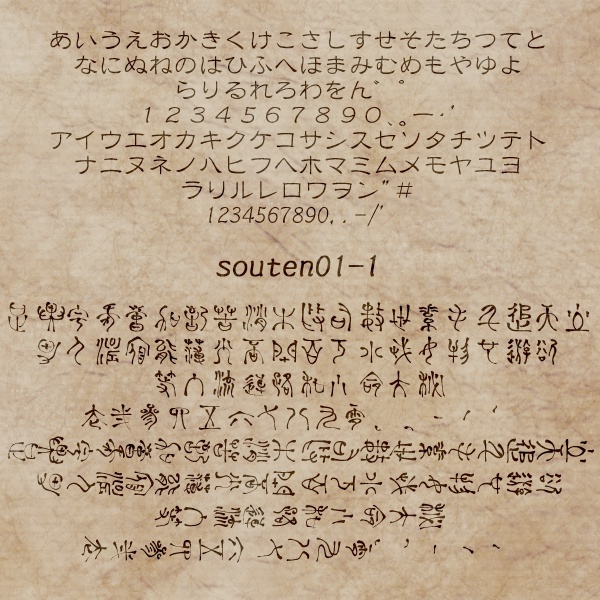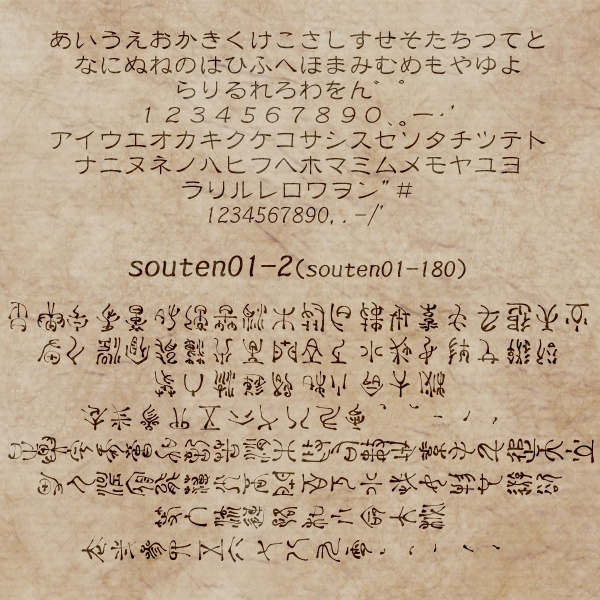
異国語・呪文フォント「souten01」
CLIP STUDIO ASSETSで配布している文字ブラシ(https://assets.clip-studio.com/ja-jp/detail?id=1708036)をフォント化したものです。 万葉仮名(使用頻度の低いもの有り)をベースとし、一部に別の文字を採用した、東洋系の言語っぽい文字列を作成するためのフォント(OpenTypeフォント)です。 書体は篆書などをベースに一部アレンジして作成しています。 「かな・全角数字・一部記号」と「カナ・半角数字・一部記号」で90°回転したものを収録しています(souten01-1:0°・90°、souten01-2:180°・270°)。 【注意事項】 著作権は放棄しておりません。 意匠・商標登録などに使用することはご遠慮ください。 フォントデータの販売・再配布もご遠慮ください。 その他の使用についてはご自由に。 また、当フォントの使用により損害などが生じても、一切の責任を負いませんのでご了承ください。 【タイプ可能な文字】 ・0°、180°回転 あいうえお かきくけこ さしすせそ たちつてと なにぬねの はひふへほ まみむめも やゆよ らりるれろ わをん ゛゜ 1234567890、。ー・’ ・90°、270°回転 アイウエオ カキクケコ サシスセソ タチツテト ナニヌネノ ハヒフヘホ マミムメモ ヤユヨ ラリルレロ ワヲン ”# 1234567890,.-/'